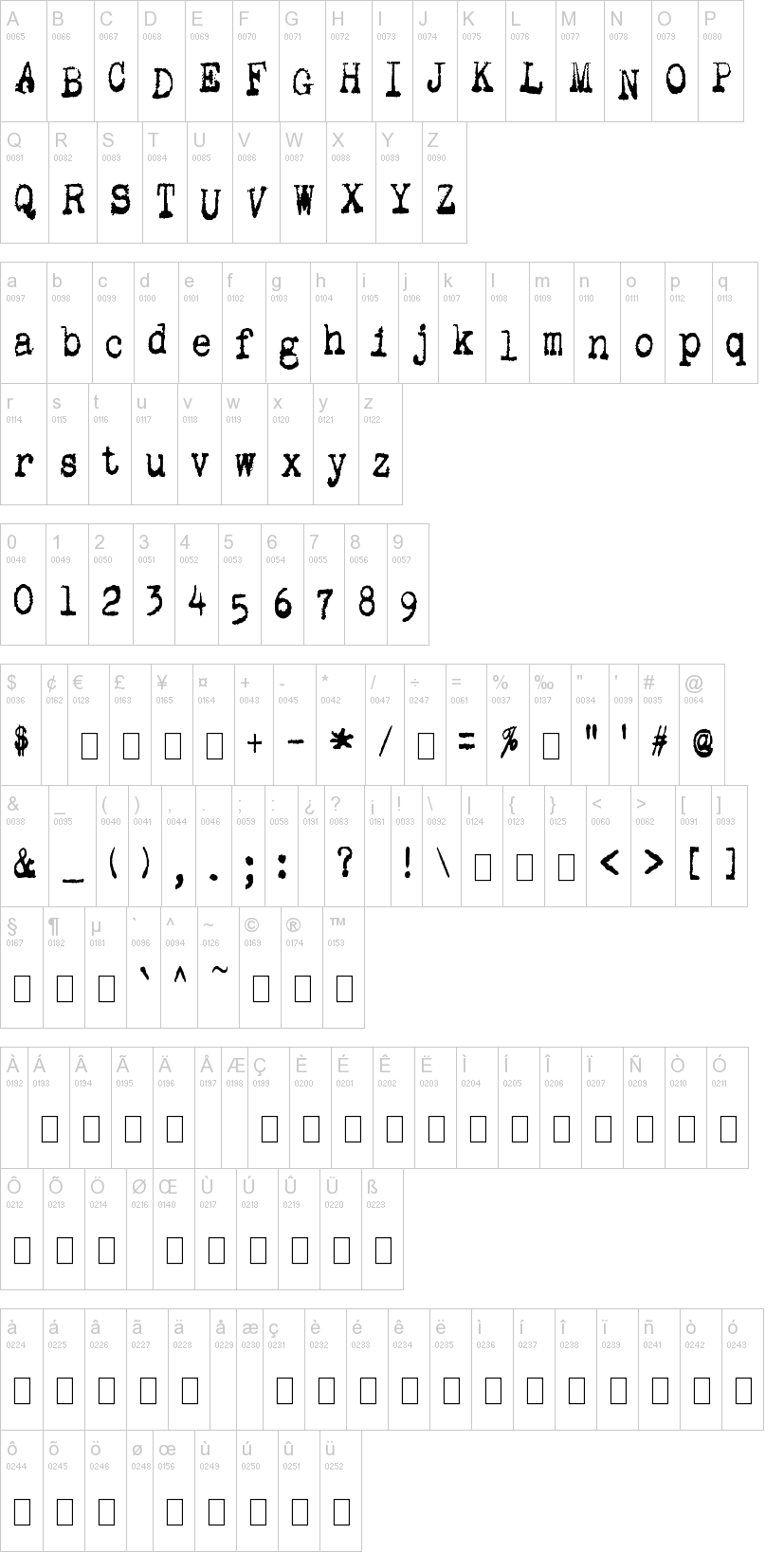
Gutter Vomit 字体是一款非常粗犷的街头风格的字体,它拥有一种独特的复古外观,将粗犷的街头风格与现代设计结合在一起。它的字母形状充满了力量,拥有比较大的空间,有助于创造出一种独特的外观效果。同时,它也具有较强的可读性,可以清晰地表达出您要传达的信息。内容介绍
Gutter Vomit是一款非常不错的手写艺术字体,具有很好的视觉感,适合于文化类的宣传设计、商业类品牌的广告和产品包装设计以及个性化文字排版等较多场景。